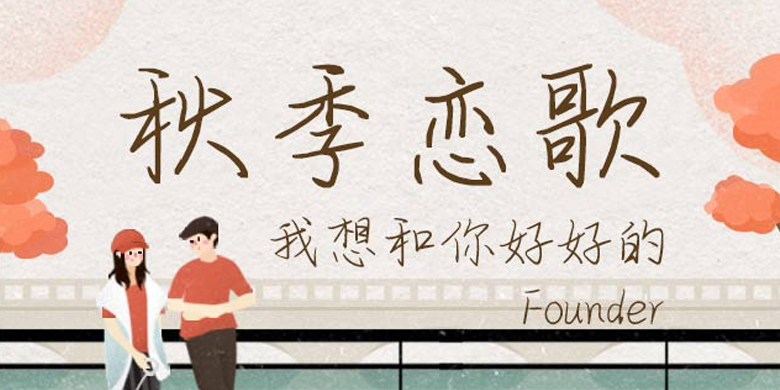
方正手迹-秋季恋歌
方正手迹-秋季恋歌,这款字体结构工整、笔画清晰,兼顾美观与易读性,适用于标题、正文、海报、包装、LOGO 等多种场景。字形优雅稳定,风格百搭耐看,适配日常排版与创意设计,让文字呈现更舒适、更具质感。方正手迹-秋季恋歌一笔一画,皆是细节,以均衡的比例、流畅的线条打造舒适视觉体验,字形端正大气,风格简约现代。无论是商业设计、品牌宣传还是日常排版,都能轻松驾驭,让文字更有格调与力量。方正手迹-秋季恋歌字体下载。
字体品牌: 方正手迹 设计师:余丹 字体分类:创意书写 字体属性:精品字 字符集:大陆简体(GB2312-80) 发布时间: 2020
变化多端的走势,略带连笔,微小的粗细变化,排版起来,看着相当舒适。适用于现代诗歌、短文的排版以及文化、商业类品牌的广告语设计。